Diterbitkan: 2023-07-25Apakah Anda seorang desainer grafis yang sedang mencari font techno yang sempurna untuk menyempurnakan proyek Anda? Tidak perlu mencari lagi, karena, dalam posting blog ini, kami telah menyusun daftar 22 font techno terbaik untuk tahun 2023, tersedia opsi gratis dan premium.
Tapi Anda mungkin bertanya-tanya, mengapa saya harus repot dengan font techno? Baiklah, izinkan kami meyakinkan Anda bahwa font yang tepat dapat membuat semua perbedaan dalam keseluruhan desain dan dampak proyek Anda.
Jadi, apakah Anda sedang mendesain situs web futuristik, logo mutakhir, atau poster yang menarik, font techno ini pasti akan meningkatkan pekerjaan Anda ke level berikutnya.
Sekarang setelah kami mendapatkan perhatian Anda, mari selami dunia font techno yang menarik. Dengan daftar lengkap yang menampilkan 22 font yang dipilih dengan cermat, Anda akan memiliki banyak opsi untuk dipilih.
Setiap font menghadirkan gaya uniknya sendiri, mulai dari ramping dan minimalis hingga berani dan ekspresif. Apakah Anda lebih suka tampilan tekno yang lebih tradisional atau ingin bereksperimen dengan sesuatu yang lebih avant-garde, kami siap membantu Anda.
Namun bukan itu saja – bagian terbaiknya adalah kami telah mengkurasi campuran font gratis dan premium, jadi Anda akan menemukan sesuatu yang sesuai dengan setiap anggaran.
Kami memahami bahwa sebagai desainer grafis, Anda mungkin tidak selalu memiliki dana untuk berinvestasi pada font premium, oleh karena itu kami memastikan untuk menyertakan opsi gratis berkualitas tinggi juga.
Jadi, berapa pun anggaran Anda, Anda masih dapat mengakses font techno terbaik yang akan meningkatkan proyek desain Anda.
mari kita mulai dan bawa desain Anda ke level selanjutnya dengan font techno mutakhir ini!
Font Techno Premium Terbaik
Ingin menambahkan sentuhan futuristik pada desain Anda? Tidak terlihat lagi dari pilihan Font Techno premium terbaik kami. Bersiaplah untuk membawa proyek Anda ke tingkat selanjutnya dengan tipografi mutakhir yang dijamin akan memikat audiens Anda.
Jangan lewatkan menemukan font yang sempurna untuk usaha kreatif Anda berikutnya – selami artikel kami dan jelajahi opsi yang harus dimiliki ini.
Oversa
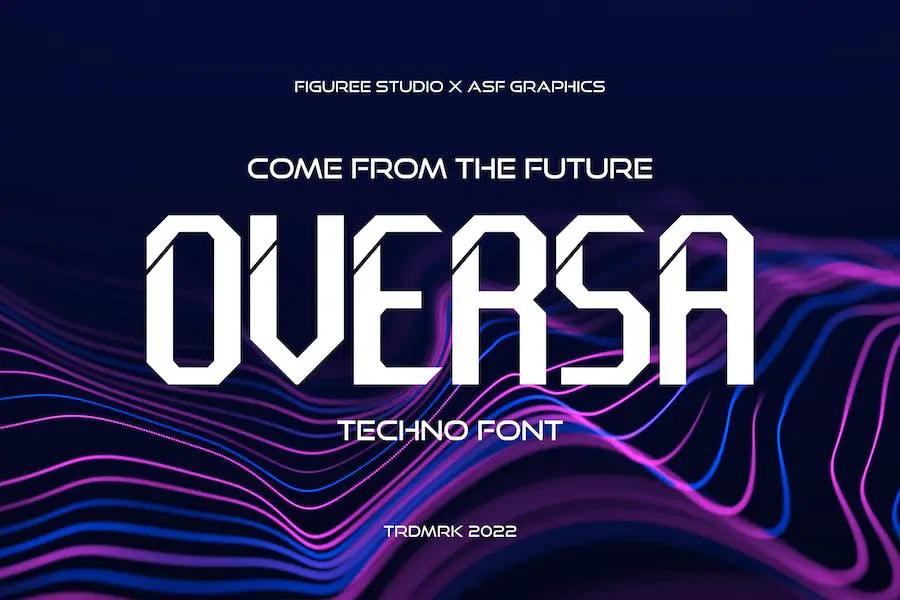
Oversa adalah font mutakhir yang menawarkan karakter huruf besar dan kecil, bersama dengan kumpulan angka. Ini membanggakan desain yang khas dan futuristik, dengan alternatif galaksi dan tema techno.
Font ini membawa Anda dalam perjalanan melalui waktu, cocok untuk poster film yang berlatar luar angkasa atau masa depan. Ini adalah pilihan ideal bagi penggemar sci-fi yang ingin membuat kartu unik dan karya seni yang dipersonalisasi.
Tapi mengapa berhenti di situ? Oversa juga dapat digunakan untuk proyek UX/UI dan techno, memungkinkan Anda untuk memberikan gambaran sekilas tentang apa yang akan terjadi di masa depan.
Mc Fredy
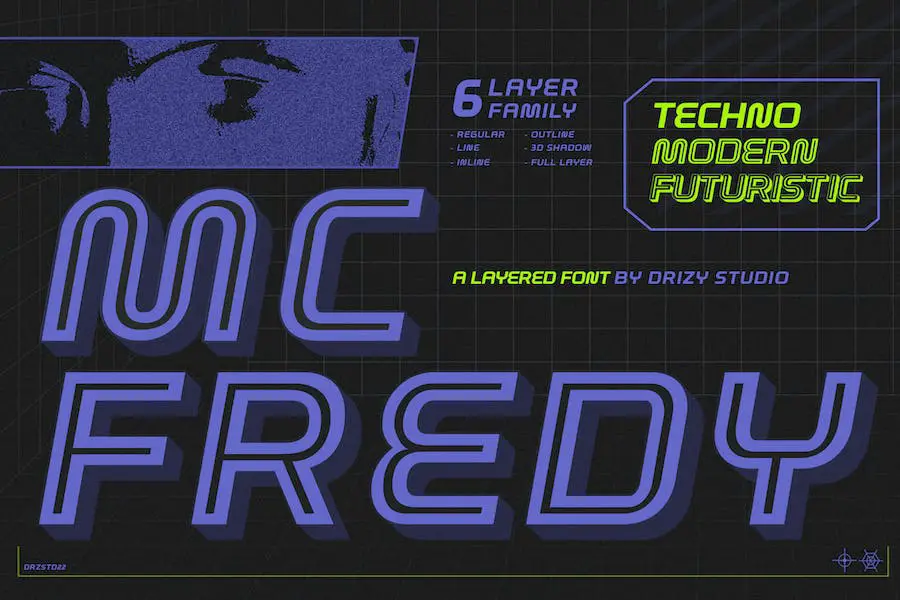
Mc Fredy adalah Font Techno Berlapis yang menakjubkan dari Drizy Studio. Dengan desainnya yang ramping dan futuristik, font ini adalah pilihan sempurna bagi desainer grafis yang ingin membawa proyek mereka ke level berikutnya.
Mc Fredy menawarkan semua gaya yang Anda butuhkan untuk membuat desain yang mencolok secara visual. Apakah Anda sedang mengerjakan logo, situs web, atau postingan media sosial, font ini siap membantu Anda.
Jamal
Jamal adalah font Techno yang kuat dan unik yang akan membawa proyek desain Anda ke level berikutnya. Apakah Anda seorang desainer grafis yang ingin menambahkan sentuhan edgy pada pekerjaan Anda atau seseorang yang mencari font yang sempurna untuk tato atau postingan Instagram, Jamal siap membantu Anda.
Dengan tampilannya yang berani dan autentik, Jamal sangat cocok untuk proyek branding apa pun, mulai dari desain logo hingga pencetakan t-shirt dan bahkan grafis esports. Desain futuristik dan garis ramping membuatnya ideal untuk menciptakan tampilan modern dan mutakhir.
Apakah Anda seorang DJ yang mencari font yang sempurna untuk materi promosi Anda atau perusahaan teknologi yang membutuhkan font yang menangkap esensi merek Anda, Jamal adalah pilihan yang tepat. Gayanya yang terinspirasi tekno akan menghadirkan kegembiraan dan energi untuk proyek apa pun.
Zona perang
Warzone adalah font techno keren dan modern yang menghadirkan sentuhan minimalis pada desain Anda. Dengan desain sans-serif dan tepi tajam, ini mewujudkan gaya ramping dan futuristik yang Anda cari.
Font ini juga menawarkan karakter alternatif ekstra, memberi Anda lebih banyak kemungkinan kreatif. Apakah Anda sedang mengerjakan proyek bertema techno, digital, sci-fi, atau hipster, Warzone adalah pilihan yang sempurna.